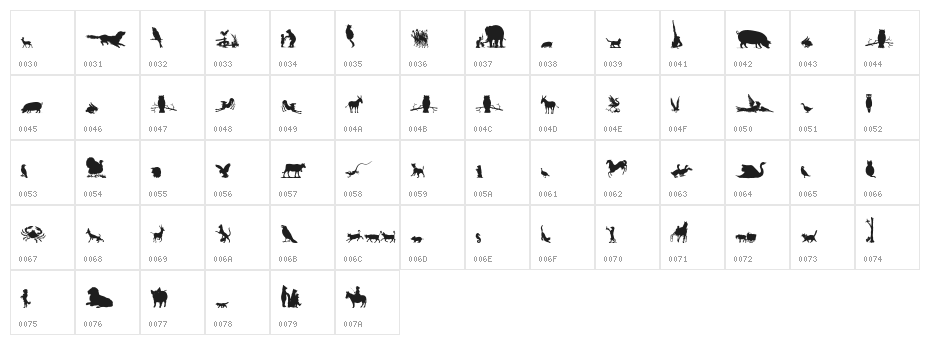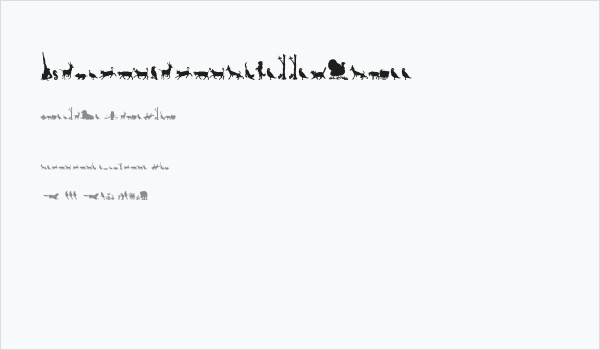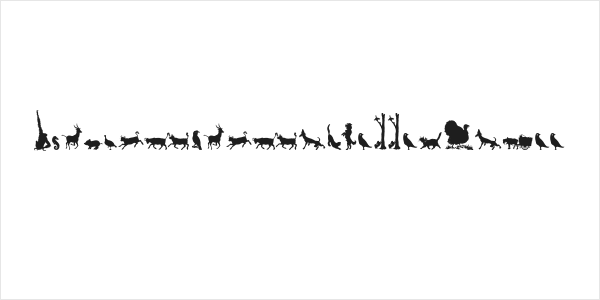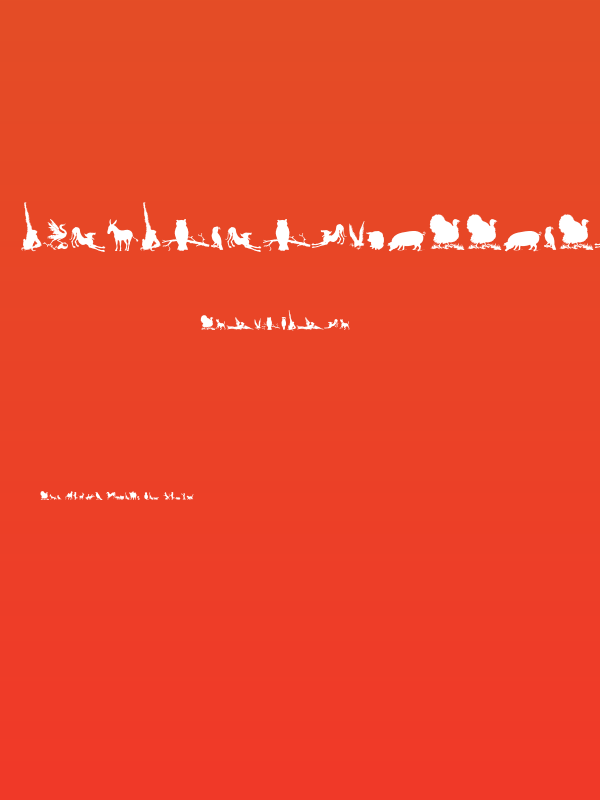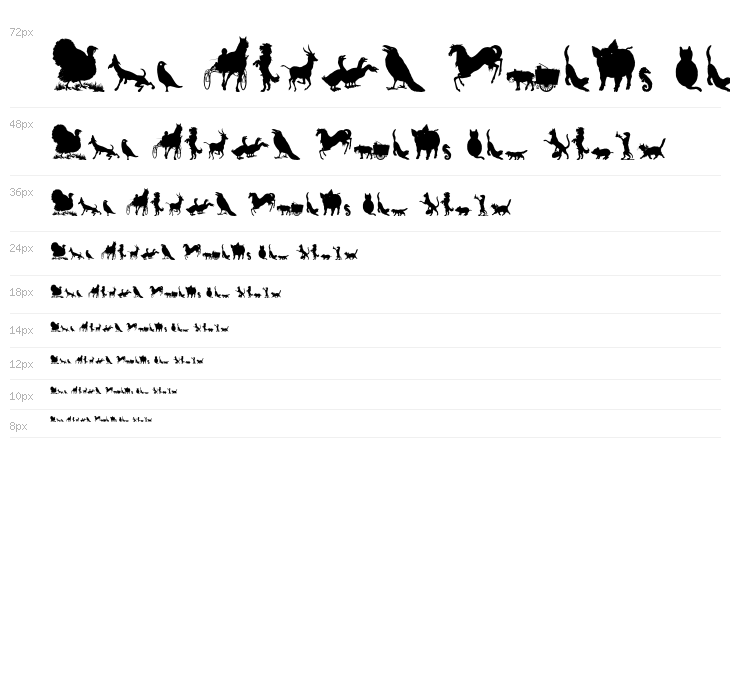
AnimalSilhouettesThree Font
| Stile generale | Decorative, illustrative |
| Caso d'uso | Decorative elements, icons, thematic design accents |
| Progetti proposti | Use in nature-themed designs, educational materials, children's books, posters, logos, and decorative elements in print or digital media. |